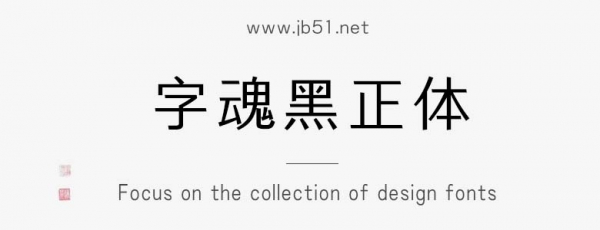
字魂黑正體由字魂字庫推出的黑體字體,該字體包含7144個(gè)中文、字母、 符號(hào)和數(shù)字,具有嚴(yán)肅商務(wù)的風(fēng)格,可以滿足您設(shè)計(jì)上的各種需求,適合應(yīng)用于藝術(shù)設(shè)計(jì)、平面宣傳設(shè)計(jì)、網(wǎng)頁設(shè)計(jì),書法字帖等領(lǐng)域。
字魂黑正體字體是一款商用的黑體,基礎(chǔ),正文字體,該字體包含7144個(gè)中文、字母、 符號(hào)和數(shù)字,具有嚴(yán)肅商務(wù)的風(fēng)格,可以滿足您設(shè)計(jì)上的各種需求,該字體主要用于嵌入式字體等場(chǎng)景, 您不但可以在字魂網(wǎng)下載字魂黑正體字體,同時(shí)還有眾多毛筆書法字體、創(chuàng)意字體等可供選擇!